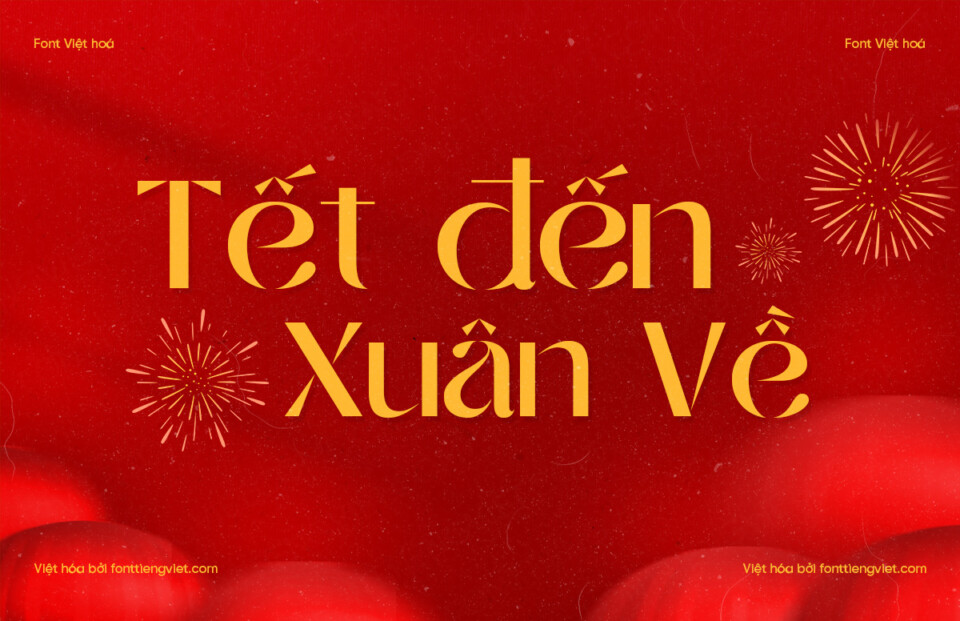
Font Việt hóa 1FTV VIP Ceraso – Font tết
Giới thiệu về Font Việt hóa 1FTV VIP Ceraso – Font tết trong thiết kế
Trong thị trường sáng tạo nội dung hiện nay, việc tìm kiếm một bộ Font Miễn Phí chất lượng cao để phục vụ cho mùa lễ hội luôn là ưu tiên hàng đầu của các nhà thiết kế. Font Việt hóa 1FTV VIP Ceraso – Font tết nổi lên như một lựa chọn hoàn hảo nhờ sự kết hợp tinh tế giữa nét đẹp truyền thống và hơi thở hiện đại. Đây là bộ font chữ được tinh chỉnh kỹ lưỡng về dấu tiếng Việt, đảm bảo tính thẩm mỹ cao nhất khi ứng dụng vào các ấn phẩm truyền thông Tết Nguyên Đán tại Việt Nam. Với đường nét thanh mảnh nhưng chắc chắn, bộ font này mang đến cảm giác ấm cúng, may mắn và thịnh vượng cho mọi khung hình thiết kế.
Đặc điểm nổi bật của Font Việt hóa 1FTV VIP Ceraso – Font tết
Phong cách thiết kế độc đáo và linh hoạt
Font Việt hóa 1FTV VIP Ceraso – Font tết sở hữu cấu trúc ký tự hài hòa, tạo nên sự cân đối tuyệt vời giữa các khoảng trắng và nét vẽ. Điểm đặc biệt của bộ font này chính là sự linh hoạt trong sử dụng, từ các tiêu đề lớn trên băng rôn, poster cho đến các đoạn văn bản ngắn trên thiệp chúc mừng. Sự tinh tế trong cách xử lý các nét móc và dấu câu giúp người dùng không còn lo lắng về lỗi hiển thị khi soạn thảo tiếng Việt, một vấn đề thường gặp ở các font quốc tế chưa được tối ưu hóa.
Tính ứng dụng cao trong mùa lễ hội
Khi nhắc đến Font Việt hóa 1FTV VIP Ceraso – Font tết, chúng ta không thể bỏ qua khả năng ứng dụng đa dạng của nó. Bạn có thể sử dụng bộ font này để thiết kế bao lì xì, menu nhà hàng dịp cuối năm hay thậm chí là các bài đăng trên mạng xã hội nhằm tăng tính tương tác. Font chữ này không chỉ đơn thuần là công cụ truyền tải thông tin mà còn là linh hồn của tác phẩm, giúp khơi gợi cảm xúc vui tươi, hân hoan của ngày Tết cổ truyền một cách tự nhiên và sâu sắc nhất đối với người xem.
Cách tối ưu hóa Font Việt hóa 1FTV VIP Ceraso – Font tết cho dự án
Kết hợp màu sắc và bố cục chuyên nghiệp
Để Font Việt hóa 1FTV VIP Ceraso – Font tết phát huy tối đa vẻ đẹp, các nhà thiết kế nên ưu tiên kết hợp với những gam màu nóng như đỏ, vàng đồng hoặc xanh lá cây đậm. Những màu sắc này khi đi cùng đường nét thanh thoát của font sẽ tạo nên hiệu ứng thị giác mạnh mẽ. Ngoài ra, việc điều chỉnh khoảng cách dòng (leading) và khoảng cách chữ (kerning) một cách hợp lý sẽ giúp thông điệp của bạn trở nên dễ đọc và chuyên nghiệp hơn, thu hút sự chú ý của khách hàng ngay từ cái nhìn đầu tiên.
Kết luận về bộ Font Việt hóa 1FTV VIP Ceraso – Font tết